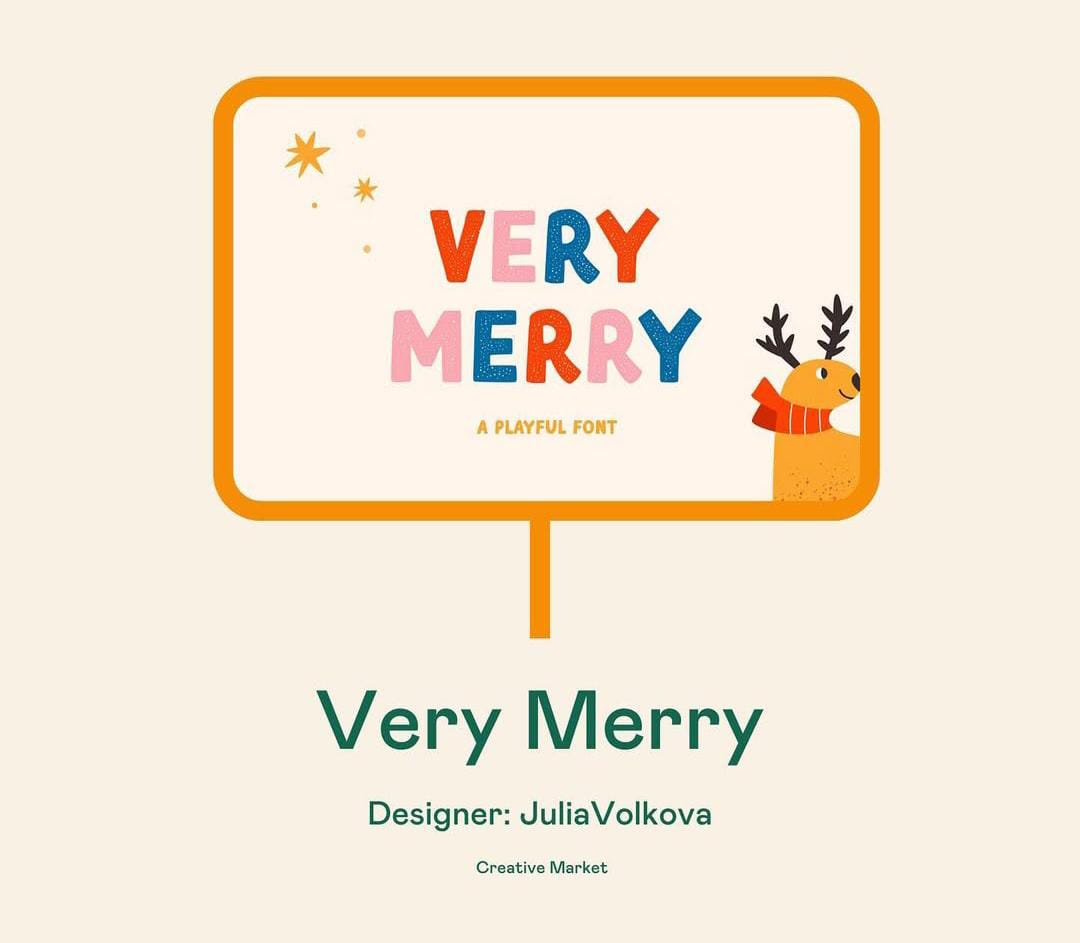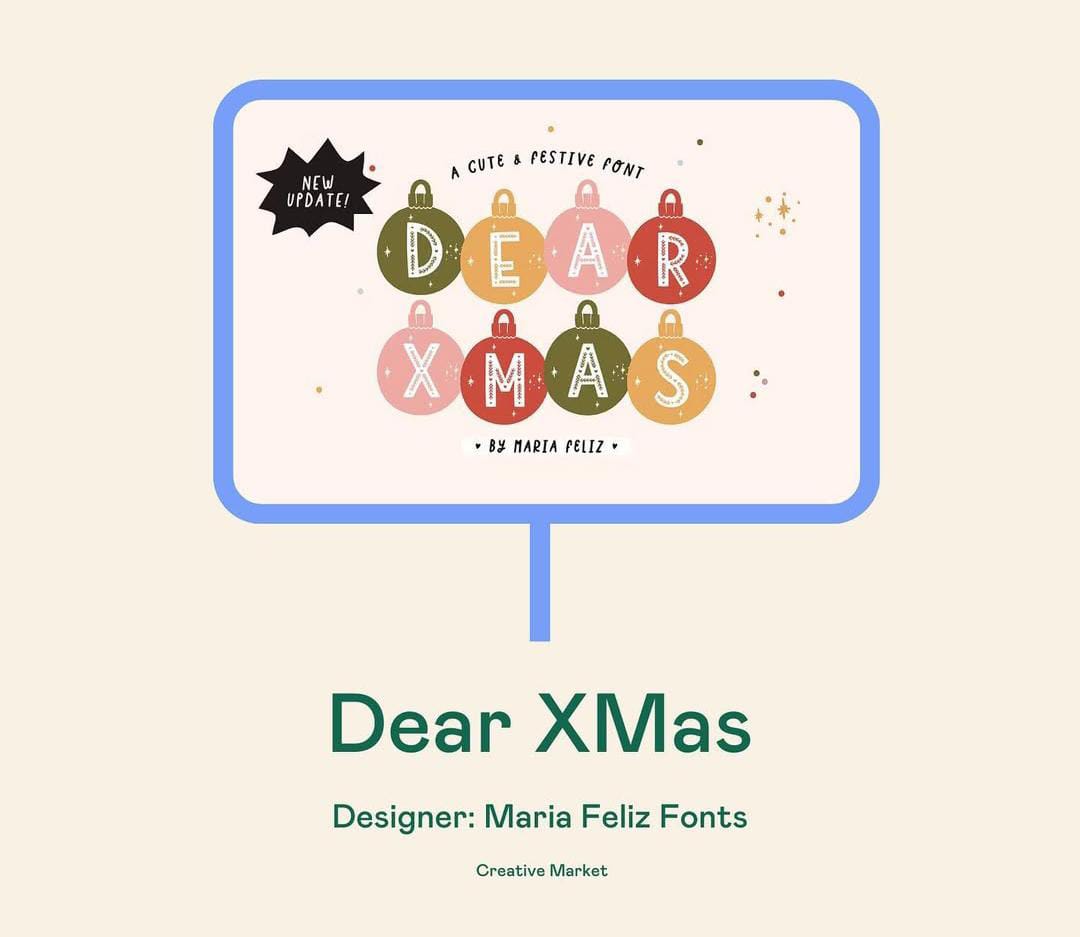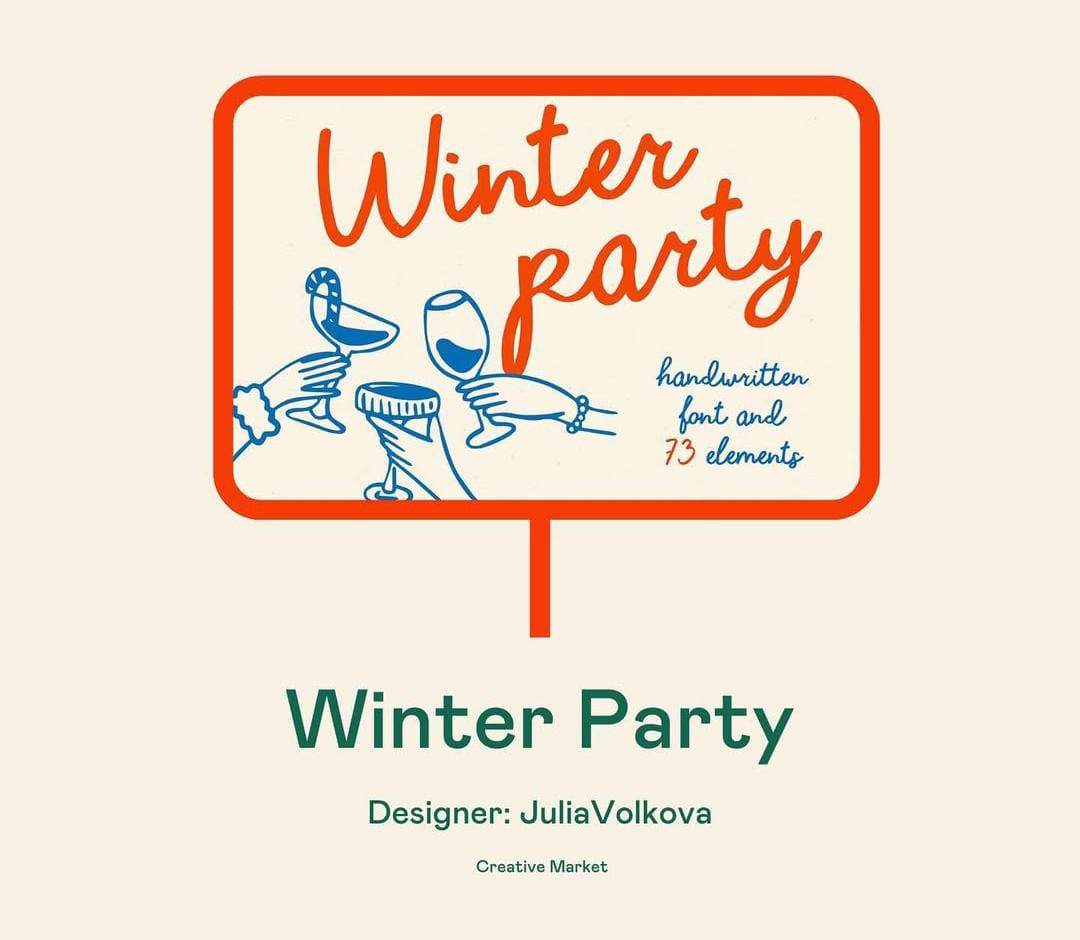
Perayaan akhir tahun akan segera tiba, saatnya desainer dan konten kreator menyiapkan desain bertema liburan yang menarik. Desain bertema holiday biasanya akan tampil bahagia, ceria, penuh warna dan menyenangkan, termasuk dengan memilih elemen yang tepat. Untuk merancang desain holiday yang menyenangkan gunakan font yang bertema natal, unik dan bergaya bebas.
TEMA DESAIN HOLIDAY
Akhir tahun identik dengan perayaan Natal dan tahun baru, desain grafis untuk poster, banner, hingga konten media sosial mulai berganti tema dari halloween. Tema desain liburan akhir tahun akan memiliki ciri dekorasi yang meriah dan penuh warna. Selain memiliki ciri desain grafis seperti:
Kombinasi Warna Cerah
Untuk kombinasi warna yang mencerminkan desain bertema tahun baru biasanya seperti warna merah, hijau, biru, putih dan oranye. Kombinasi beberapa warna cerah yang terinspirasi dari natal dan kembang api akan tampil menarik. Desain grafis yang penuh warna akan mencerminkan kesan ceria, bahagia dan menyenangkan, relevan untuk desain perayaan.
Warna-warna cerah biasanya digunakan untuk warna dekorasi seperti gambar lampu atau gambar kembang api. Terkadang font untuk desain bertema holiday akan memiliki warna-warni. Setiap huruf diberi warna berbeda akan berkesan lebih ceria dan menyenangkan.
Dekorasi Elemen Natal
Desain grafis bertema liburan akhir tahun juga banyak menggunakan dekorasi elemen natal. Gambar elemen yang identik dengan natal adalah pohon natal, lampu natal, santa, rusa hingga pernak-pernik lainnya. Kombinasi elemen gambar natal, warna cerah dan font playful akan relevan untuk desain holiday akhir tahun yang menyenangkan.
Gambar-gambar tersebut biasanya memiliki warna yang cerah juga sehingga tampil lebih mencolok. Pastikan palet warna tetap diatur dengan harmonis sehingga desain yang meriah tidak terlihat berantakan. Elemen visual tersebut akan mencerminkan kebahagiaan dalam menyambut tahun baru.
Tipografi Fun dan Playful
Untuk mendukung kesan bahagia dan menyenangkan, penting untuk menggunakan font yang menyenangkan dan fun. Jenis font yang fun dan playful akan relevan dengan perayaan tahun baru. Pilih gaya font tebal, bulat, dan bergaya bebas untuk desain tema holiday.
Font display dan handwritten juga akan cocok mencerminkan kesan menyenangkan. Selain font bulat, tata letak yang tidak beraturan juga akan cocok. Ada juga tema font Natal dengan dekorasi natal yang meriah dapat digunakan untuk tema desain tersebut.
Gambar Dekorasi Tahun Baru
Desain grafis akhir tahun berguna merayakan pergantian tahun sehingga memiliki dekorasi yang mencerminkan akhir tahun. Untuk menyambut perayaan tahun baru, desain grafis akan memiliki dekorasi gambar angka tahun baru, terompet, kembang api dan lainnya. Desain harus terlihat meriah dan menyenangkan agar mencerminkan kebahagiaan.
Jika brand memiliki karakter, biasanya karakter akan didesain untuk menggunakan topi tahun baru atau dekorasi angka tahun baru. Desain grafis bertema tahun baru harus memiliki dekorasi kembang api dan elemen pesta lainnya.
REKOMENDASI FONT UNTUK DESAIN HOLIDAY
Untuk menciptakan desain tema liburan yang menyenangkan, bahagia dan ceria pilih gaya font yang relevan dan menarik. Penggunaan font bulat, serif panjang dan font dekorasi unik akan cocok untuk tema desain holiday. Berikut beberapa rekomendasi font menarik untuk desain liburan akhir tahun:
Font The Holidays
Gaya font ini memiliki huruf serif yang bersih dengan dekorasi serif panjang dan melengkung. Bentuk serif melengkung menciptakan tipografi terlihat memiliki ornamen dan bergaya menarik. Gaya font serif yang terlihat bebas dan tidak kalau menciptakan kesan menyenangkan, relevan dengan tema desain.
Font ini bisa digunakan untuk mencerminkan kesan desain holiday yang menyenangkan, magis dan ceria. Tema desain liburan dengan font tersebut bisa mencerminkan kesan magis dan bahagia. Untuk kartu ucapan atau desain kemasan hadiah, font akan tampil menarik dan relevan.
Font True Fate
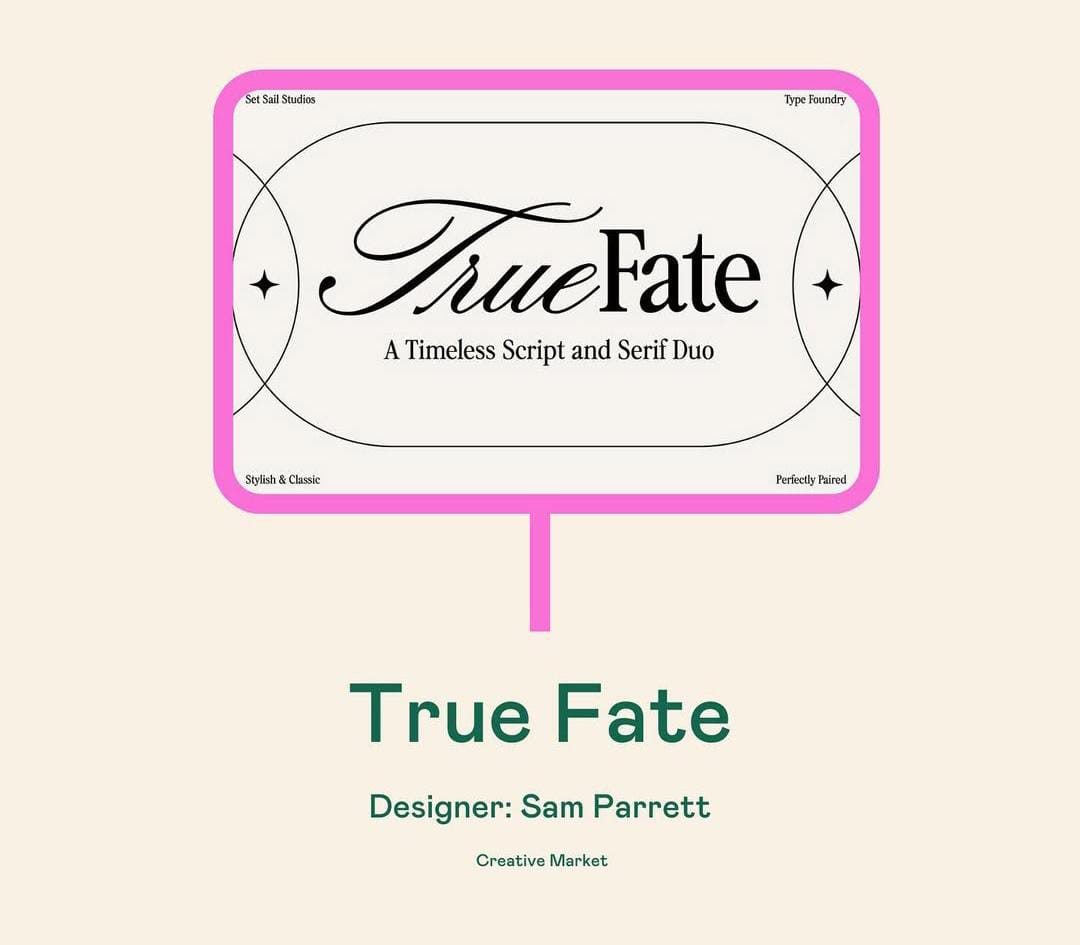
Kombinasi font dengan dua gaya berbeda akan menciptakan kontras dan desain visual yang menarik. Selain bertema meraih, desain liburan akhir tahun juga kadang berkesan magis dan ajaib. Hal ini karena orang-orang seringkali mengucapkan banyak harapan dan menginginkan kebahagiaan.
Gaya font elegan dengan serif panjang akan menciptakan kesan magis dan ajaib sesuai tema desain. Kombinasi gaya font script tipis yang panjang terlihat elegan dengan font serif yang elegan pula. Kedua font bisa mencerminkan tema desain liburan natal yang elegan dan bergaya mewah.
Font Ugly Weather
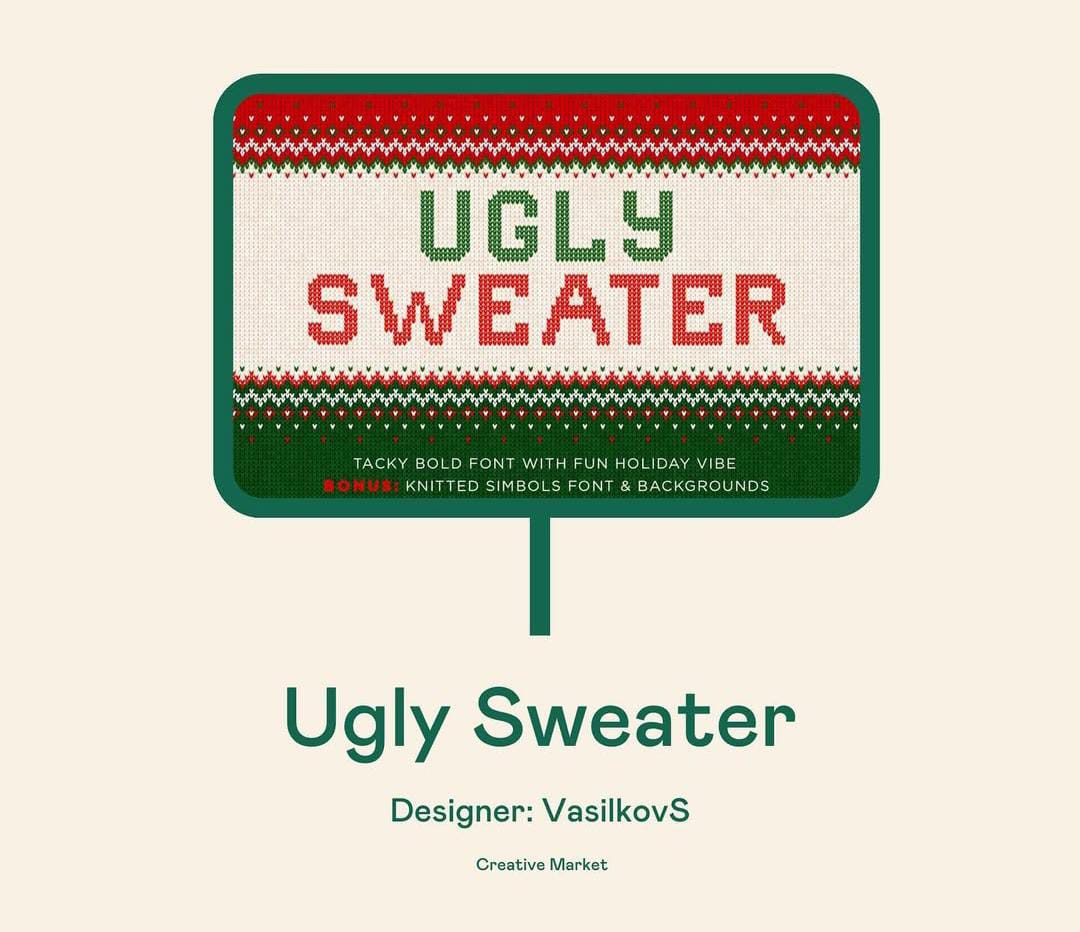
Kombinasi gaya font modern dan Y2K yang populer bisa menciptakan desain visual yang menarik. Font bergaya piksel tersebut memiliki gaya huruf yang sederhana sehingga memiliki keterbacaan yang baik. Font piksel terlihat tebal, menyenangkan dan berkesan hangat karena memiliki style seperti tekstur sweater.
Font handwritten tersebut bisa menciptakan kesan bebas kreatif dan menyenangkan. Gaya font bisa menciptakan tema desain pesta natal dan tahun baru yang elegan. Font juga memiliki keterbacaan yang baik meski memiliki huruf bersambung.
Dari beberapa rekomendasi font tersebut untuk tema desain holiday kebanyakan memiliki tema natal dan tahun baru. Font yang digunakan bisa menciptakan kesan bahagia, meriah dan suasana liburan yang menyenangkan. Pastikan memilih font yang menarik tetapi juga memiliki keterbacaan yang baik, sehingga tetap tersampaikan dengan baik.